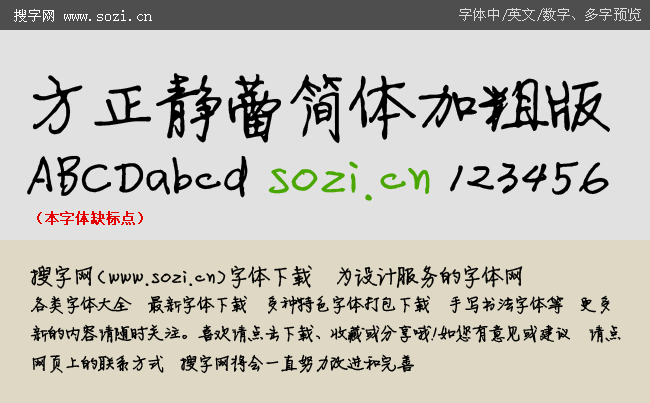
方正靜蕾簡體加粗版
搜字網(wǎng)提供一款手寫風(fēng)格的手機(jī)中文字體方正靜蕾簡體加粗版字體下載,方正靜蕾體是方正電子攜手徐靜蕾發(fā)布了其個(gè)人書法計(jì)算機(jī)字庫產(chǎn)品,字體骨骼清秀、遒勁有力,清冽而又優(yōu)雅、從容,令人賞心悅目。喜歡的朋友趕快下載吧。